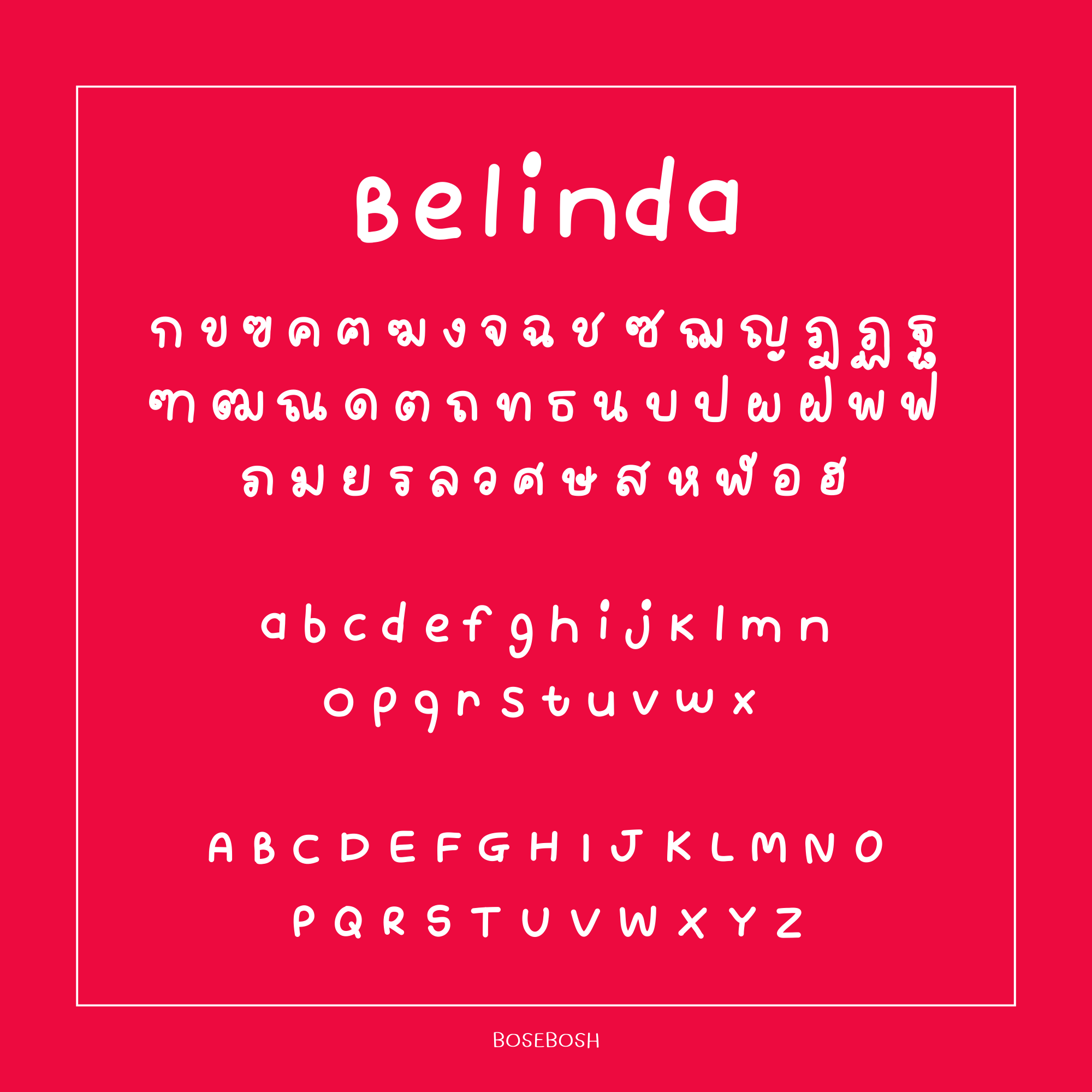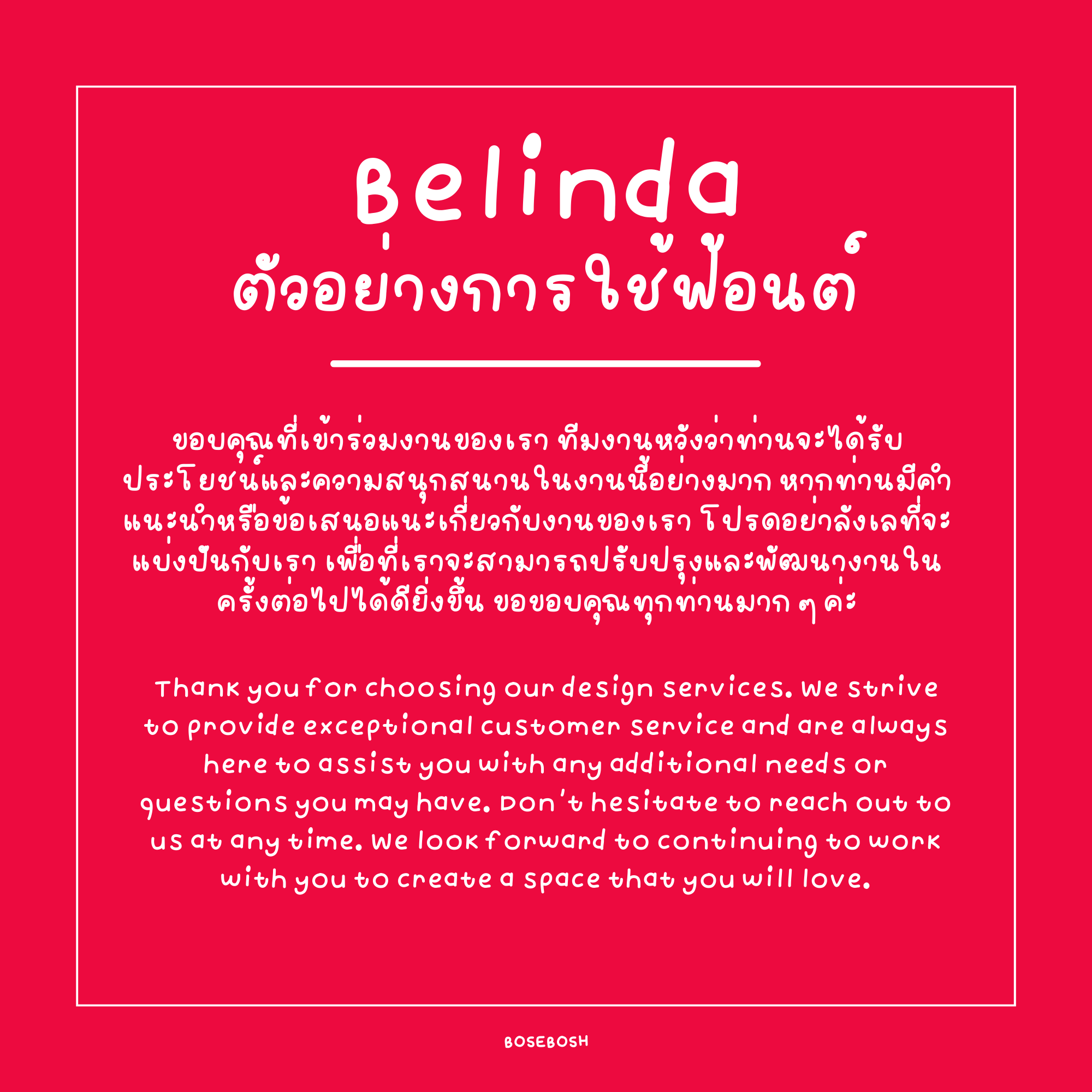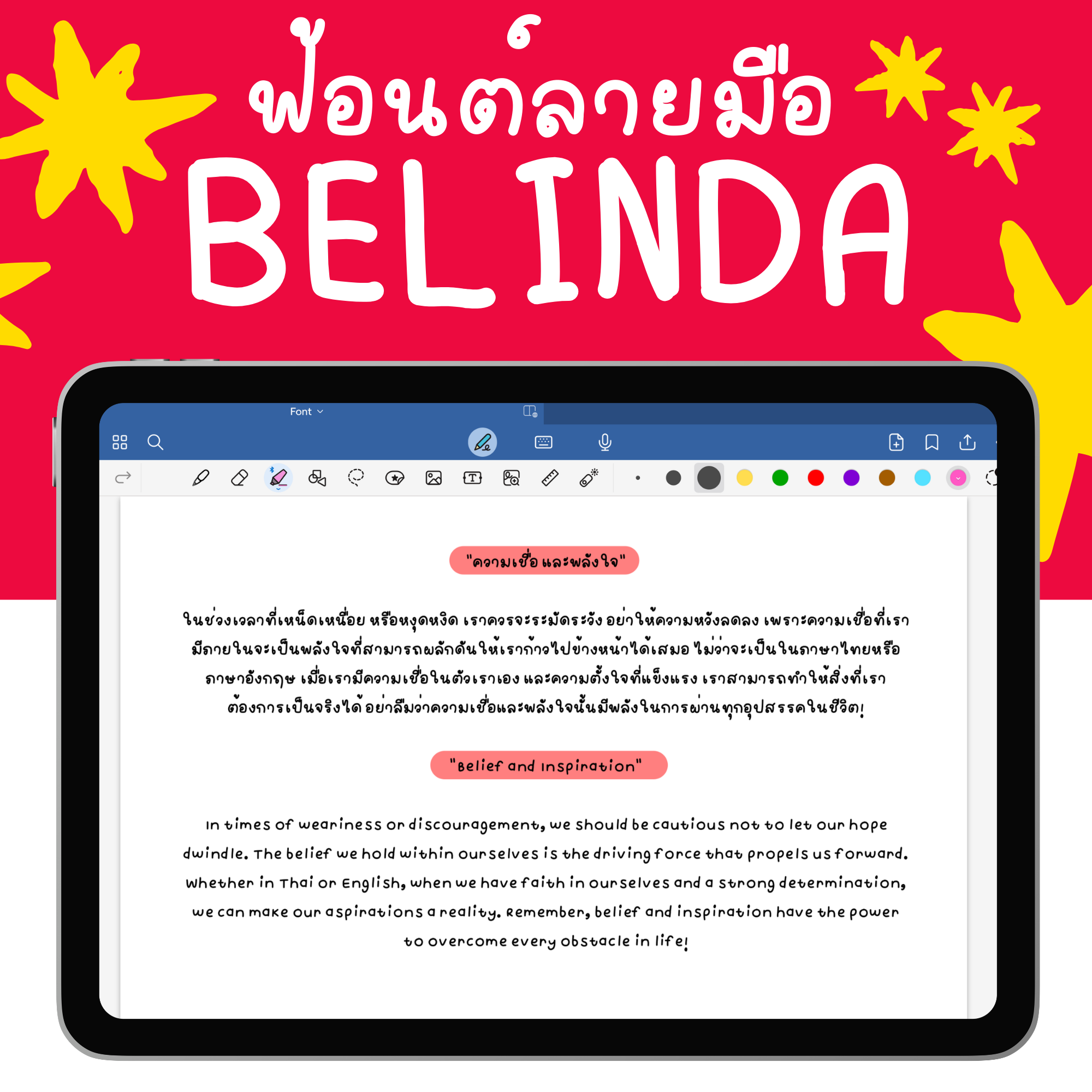
Belinda Font
✏️ Belinda — ฟอนต์ลายมือทรงกลม น่ารัก สดใส อ่านง่ายทุกตัวอักษร
💬 เส้นอักษรหนากำลังดี สื่อความนุ่มนวลเป็นกันเอง วางสระและวรรณยุกต์ได้อย่างเรียบร้อย ไม่จมไม่ลอย
🌐 รองรับทั้งภาษาไทย ภาษาอังกฤษ ตัวเลขอารบิกและเลขไทย พร้อมใช้งานในทุกอุปกรณ์ (.ttf)
💡 เหมาะกับงาน เขียนสรุปในแอปจดโน้ต GoodNotes หรือ Notability สร้างโปสเตอร์และภาพประกอบคำพูด ออกแบบงานนำเสนอหรือสไลด์ให้น่าสนใจใช้ในสื่อการเรียนรู้และงานกราฟิกแนวเด็ก ๆ หรือแนวอบอุ่น
🎀 ไม่ว่าจะใช้จดโน้ต เขียนสรุป ทำโปสเตอร์ ตกแต่งสไลด์ ทำปก หรือใส่ข้อความในวิดีโอ ก็ช่วยเพิ่มความสดใสได้ในทันที!
🖋️ ถูกออกแบบให้เหมือนลายมือจริง อ่านง่าย สบายตา
🔠 รองรับทั้งภาษาไทย ภาษาอังกฤษ ตัวเลขอารบิก และเลขไทย